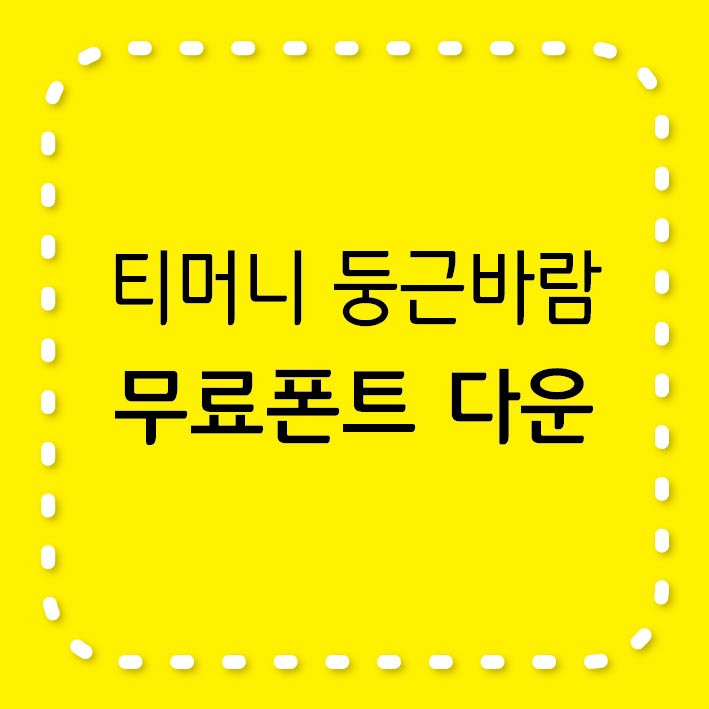
티머니 서체는 티머니 이름과 목소리에 담긴 철학과 약속입니다.
Smart - 보다 친절하고 명확하게
Mobile - 보다 편리하고 유연하게
티머니의 핵심상징 'T'를 연결점으로 심복마크 + 로고타입으로 구성되었습니다.
티머니 무료 폰트 '티머니 둥근바람'은 티머니와 바람만 있으면 어디든 갈 수 있다는 명쾌한 이야기에서 시작됩니다.
티머니의 핵심 상징 'T'에서 연계한 글꼴의 둥근 형태에는 고객에 대한 티머니의 친밀한 마음과 유연함이 담겨 있습니다.
길어진 글자 이미지는 고객에게 더 깊이 다가가겠다는 티머니의 의지를 나타냅니다.
티머니 둥근바람 서체는 두 종료로 ExtraBold와 Regular입니다.